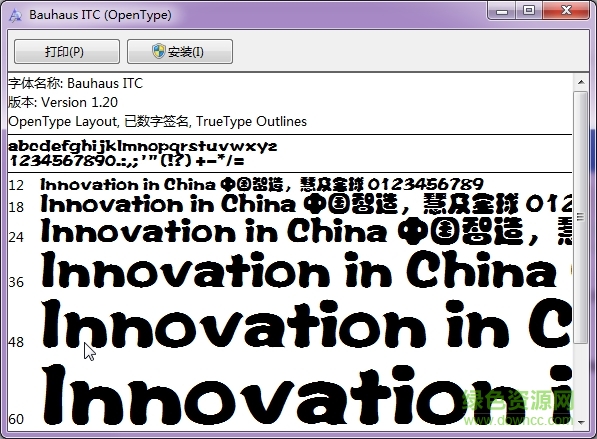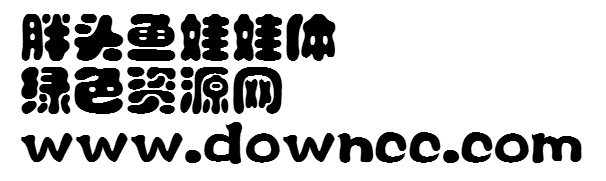
胖頭魚(yú)娃娃體是一款字形大方、粗胖的卡通字體,因形似娃娃魚(yú)而得名,讓你的文字擁有不同的風(fēng)格和更直觀的視覺(jué)體驗(yàn),綠色資源網(wǎng)歡迎大家下載使用!
胖頭魚(yú)娃娃體是從三星Galaxy Note手機(jī)中提取出來(lái)的直裝字體,字體結(jié)構(gòu)粗大健壯,比較適合視覺(jué)不好或老年人使用,同時(shí)也可以運(yùn)用在藝術(shù)設(shè)計(jì)、海報(bào)設(shè)計(jì)、名片設(shè)計(jì)等領(lǐng)域。